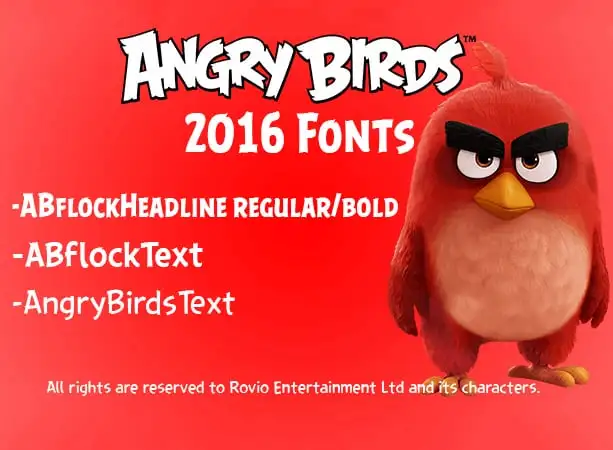
ABFlockText Font Family – Download Grátis
A ABFlockText Font Family é uma família de tipo Display que traz vida à jogabilidade dos games Angry Birds, criada pelo designer AlexBird2581 HD. Essas fontes são legítimas e foram encontradas diretamente no código-fonte do jogo, em formato APK ou IPA. A habilidade destes designers de decodificar esses arquivos revelou uma parte do mistério por trás da criação dos jogos. O software WinRAR foi fundamental para essa descoberta. A font é pertencente à Rovio Entertainment, criadora original do jogo Angry Birds. Este designer nos dá acesso a esta font exclusiva, que cativará os milhões de fãs do Angry Birds com seu design único e vibrante.